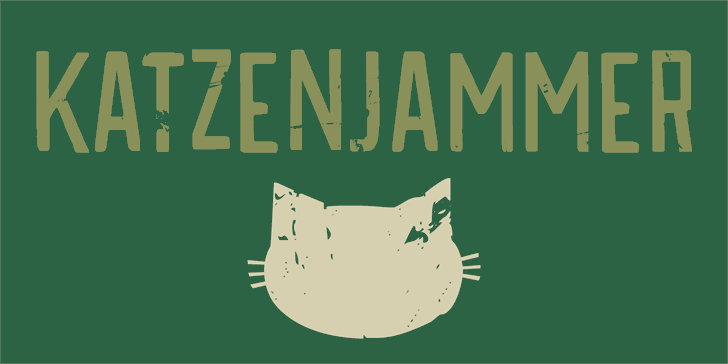
DK Katzenjammer font – Download Grátis
A DK Katzenjammer é uma linda fonte decorativa criada pelo designer Hamilton. Seu design maciço e arredondado traz à vida os textos mais elaborados, dando um toque único e vibrante aos projetos gráficos que usa. Esta versão demo serve para uso pessoal apenas. Para fins comerciais, adquira a fonte completa disponível em seu site, que inclui kerning, direitos de embedding, todos os caracteres originais além dos extras disponíveis. Evite usar a DK Katzenjammer em jogos, aplicativos ou software. Se você deseja licenciar para esses usos específicos, visite o site de Hamilton no www.hanodedfonts.com. Um FAQ incluído na pasta zip também fornecerá mais informações úteis. Com sua DK Katzenjammer, faça seus projetos brilharem ainda mais.